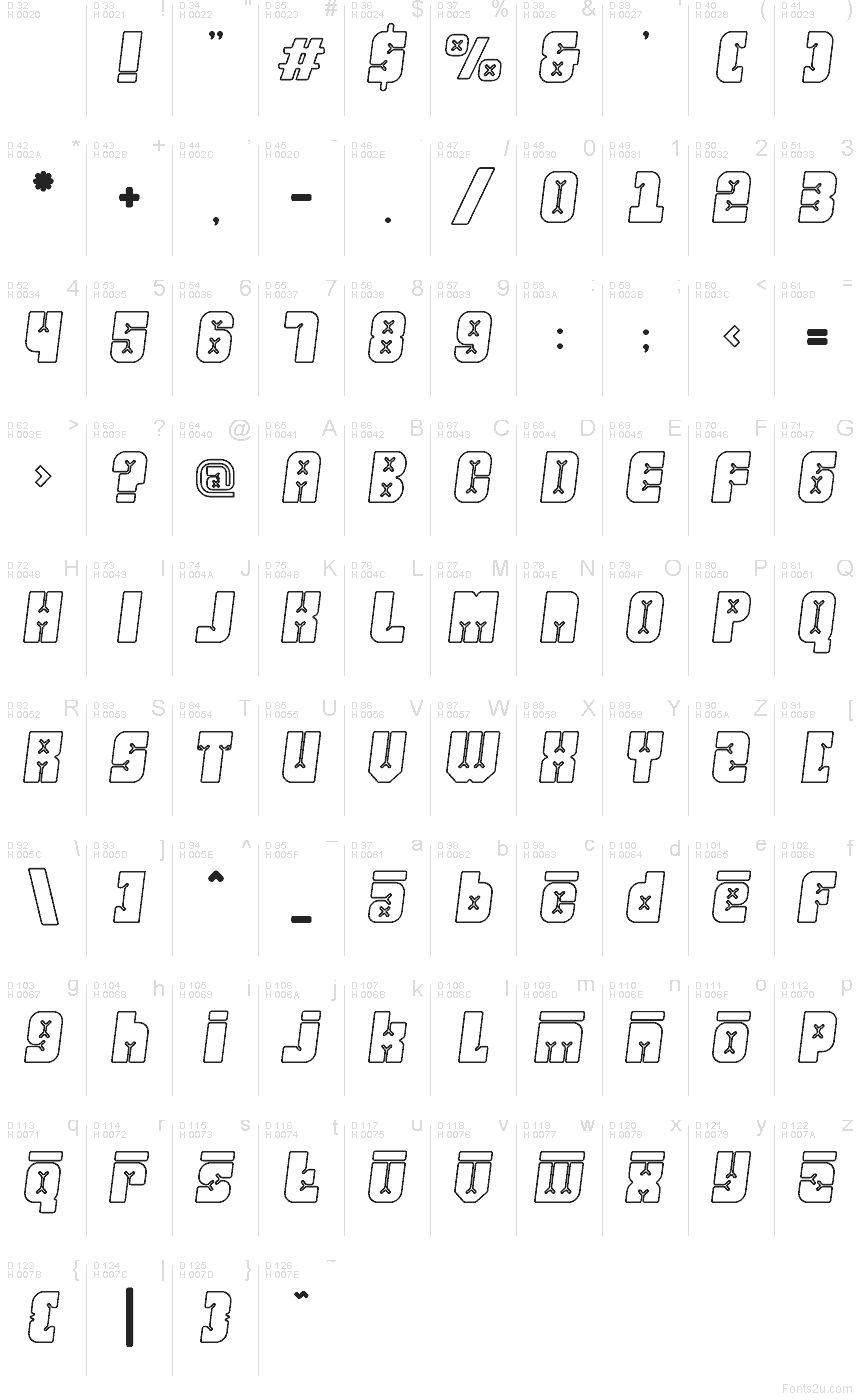
Friez Six od studia Putracetol je bezplatné, groovové, obrysové písmo typu display, které definují zaoblené blokové siluety a drobné zářezy, jež se opakují napříč znaky. Tyto vnitřní prvky brání tomu, aby písmo působilo jako obyčejné bublinové tvary, a dodávají designu hravý, téměř hračkový rytmus s jasným grafickým systémem.
Tato kombinace skvěle funguje v nadpisech plakátů, letácích na akce pro děti, návrzích samolepek, hravých obalech a krátkých logotypech, kde výrazný obrys odvádí většinu vizuální práce. Písmo se také hodí pro grafiku na sociální sítě a merchandising, zejména pokud hledáte velké, přátelské tvary s neotřelým nádechem místo standardního retro obrysu.